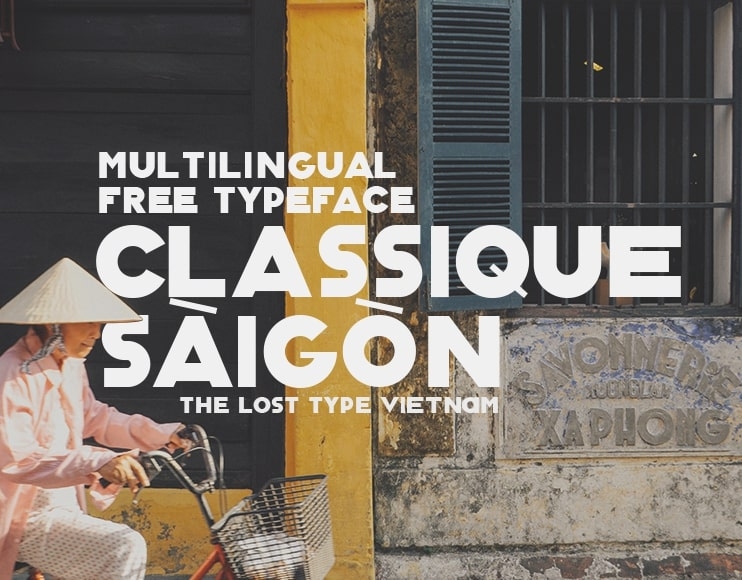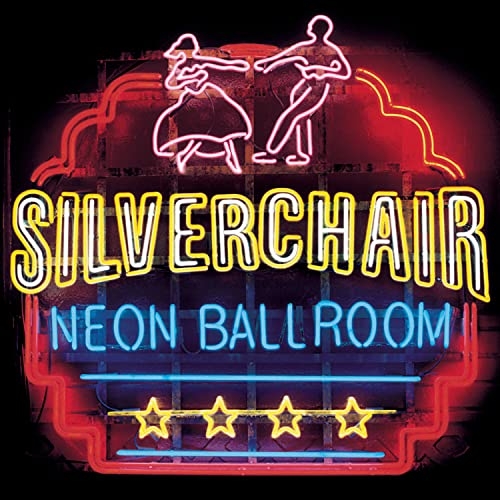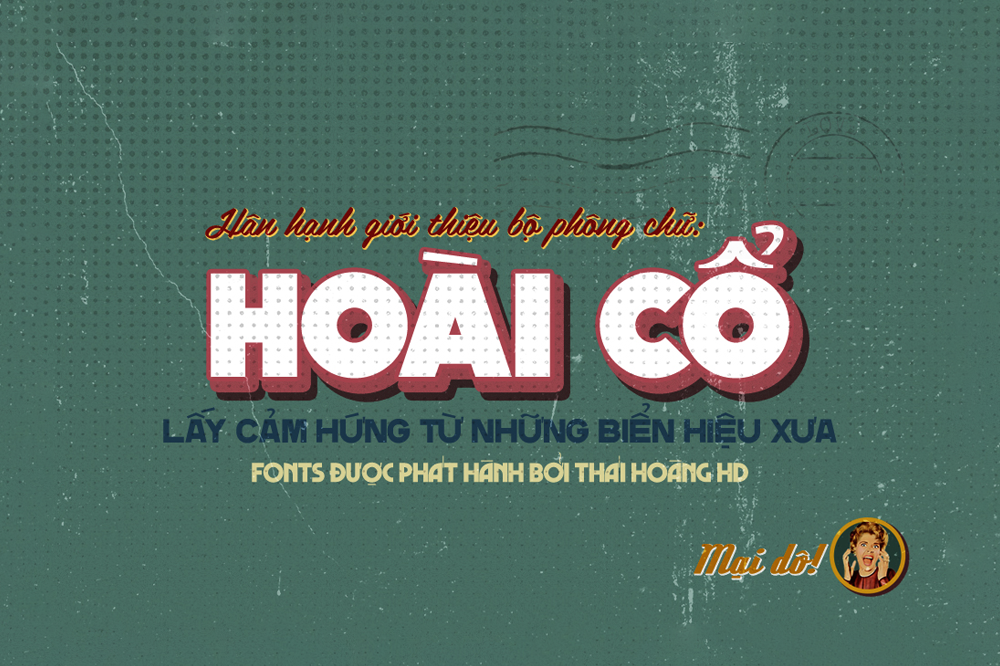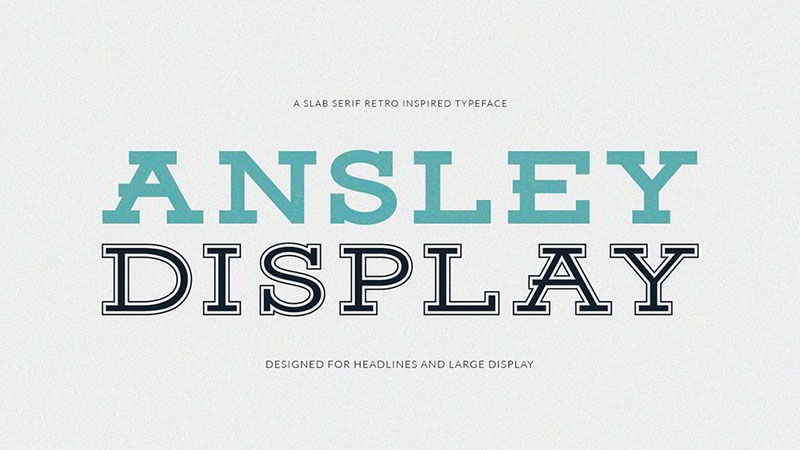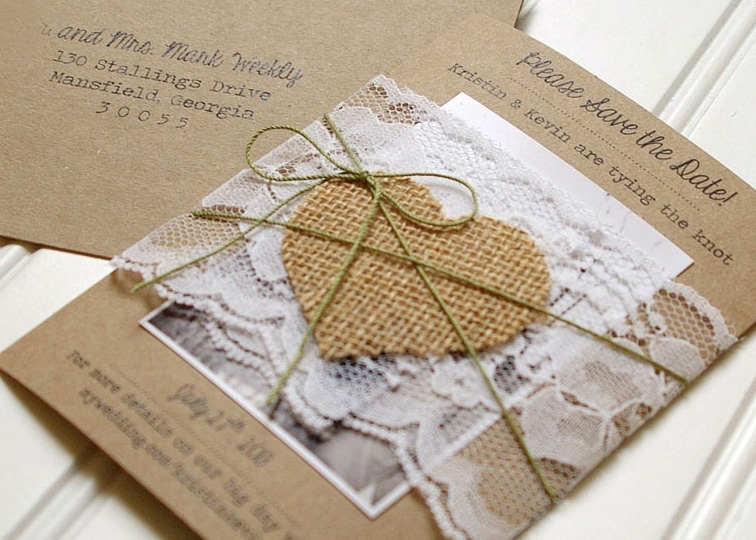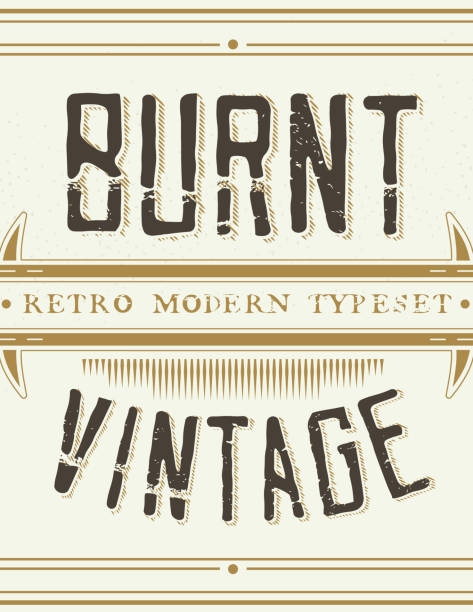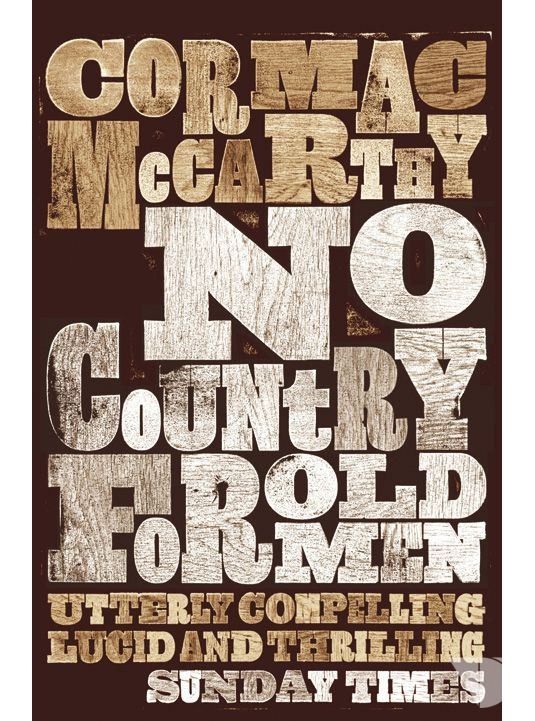
Tổng hợp 124 bộ font Vintage đẹp nhất
Font chữ Vintage mang phong cách cổ điển nhưng luôn giữ được sức hút vượt thời gian trong lĩnh vực thiết kế, đặc biệt là thiết kế đồ họa. Nếu bạn muốn tạo ra sự mới mẻ và độc đáo cho sản phẩm thiết kế của mình, thì việc áp dụng phong cách vintage sẽ là một lựa chọn đáng để thử.
Font chữ Vintage là gì?
“Vintage” trong tiếng Anh mang ý nghĩa cổ điển, xưa cũ và được ứng dụng rộng rãi trong nhiều lĩnh vực như thời trang, nội thất và đặc biệt là thiết kế đồ họa. Phong cách Vintage gợi nhớ đến những ký ức xưa cũ, mang trong mình vẻ đẹp của quá khứ và dấu ấn của thời gian. Có thể nói, Vintage không chỉ là một từ ngữ đơn thuần mà còn chứa đựng chiều sâu về thẩm mỹ, phong cách và giá trị thời gian.
Trong thiết kế đồ họa, font chữ đóng vai trò vô cùng quan trọng, góp phần định hình phong cách và cá tính cho mỗi tác phẩm. Việc lựa chọn font chữ phù hợp là yếu tố then chốt, và font chữ Vintage chính là một trong những lựa chọn nổi bật. Mang trong mình nét cổ điển pha lẫn sự tinh tế và sang trọng, font chữ Vintage luôn thu hút ánh nhìn và tạo nên dấu ấn đặc biệt.
Dù trải qua nhiều xu hướng thiết kế hiện đại, font chữ Vintage vẫn giữ vững vị thế của mình nhờ vẻ đẹp vượt thời gian. Sự kết hợp giữa phong cách cổ điển và tinh thần hiện đại trong font chữ Vintage sẽ giúp bạn tạo ra những thiết kế độc đáo, ấn tượng và đầy cảm xúc.
Một số font chữ vintage hot nhất hiện nay
Font chữ Vintage bóng đèn Neon
Font chữ Vintage bóng đèn Neon là kiểu chữ nổi bật với hiệu ứng phát sáng mô phỏng ánh sáng từ đèn Neon – hiện tượng xảy ra khi dòng điện chạy qua khí Neon. Loại font này thường được sử dụng trong các thiết kế cần sự thu hút mạnh mẽ như biển hiệu, banner quảng cáo, logo, nhãn mác, văn phòng phẩm hay thiệp mời. Sự rực rỡ của kiểu chữ này mang lại cảm giác sinh động, bắt mắt và đầy tính nghệ thuật.
Font chữ Vintage hoài cổ
Phong cách hoài cổ của font chữ Vintage là lựa chọn lý tưởng cho các thiết kế mang đậm dấu ấn lịch sử và truyền thống. Đặc biệt phù hợp trong các ấn phẩm truyền thông hướng đến văn hóa Việt Nam xưa, giai đoạn kháng chiến, hoặc những dự án cần gợi lại hình ảnh của một thời đã qua.
Font chữ Vintage lai hiện đại
Sự kết hợp giữa vẻ đẹp cổ điển và đường nét hiện đại tạo nên font chữ Vintage lai hiện đại – một lựa chọn thú vị cho những ai yêu thích sự phá cách nhưng vẫn giữ được chất cổ điển. Kiểu chữ này mang lại nét mới lạ và độc đáo, giúp thiết kế trở nên nổi bật và cuốn hút hơn.
Font chữ Vintage sang trọng
Đối với những thiết kế thiệp cưới mang hơi hướng hoài niệm nhưng vẫn muốn toát lên sự sang trọng, font chữ Vintage là sự lựa chọn hoàn hảo. Kiểu chữ này dễ dàng tạo cảm giác trang nhã, tinh tế và đầy cảm xúc cho các dịp đặc biệt như lễ cưới.
Font chữ Vintage phai mờ
Font chữ Vintage phai mờ mang đậm dấu ấn thời gian, thể hiện vẻ đẹp bền bỉ, cổ kính dù thời gian có trôi qua. Sự phai nhạt trong nét chữ như kể lại một câu chuyện lâu đời, gợi cảm giác gần gũi và sâu lắng cho người xem. Đây là kiểu chữ lý tưởng để truyền tải thông điệp về sự trường tồn và ký ức.
Vintage Retro Font with Sample Text. Handcrafted Decoration Font.
Font chữ Vintage dùng trong sách
Trong lĩnh vực xuất bản, việc lựa chọn font chữ luôn là yếu tố quan trọng để tạo ấn tượng ban đầu với độc giả. Font chữ Vintage thường được ưu ái sử dụng trong nhiều đầu sách bởi sự kết hợp hài hòa giữa vẻ đẹp cổ điển và tính hiện đại. Kiểu chữ này không chỉ giúp tạo dấu ấn riêng biệt cho ấn phẩm mà còn truyền tải cảm xúc tinh tế qua từng con chữ.